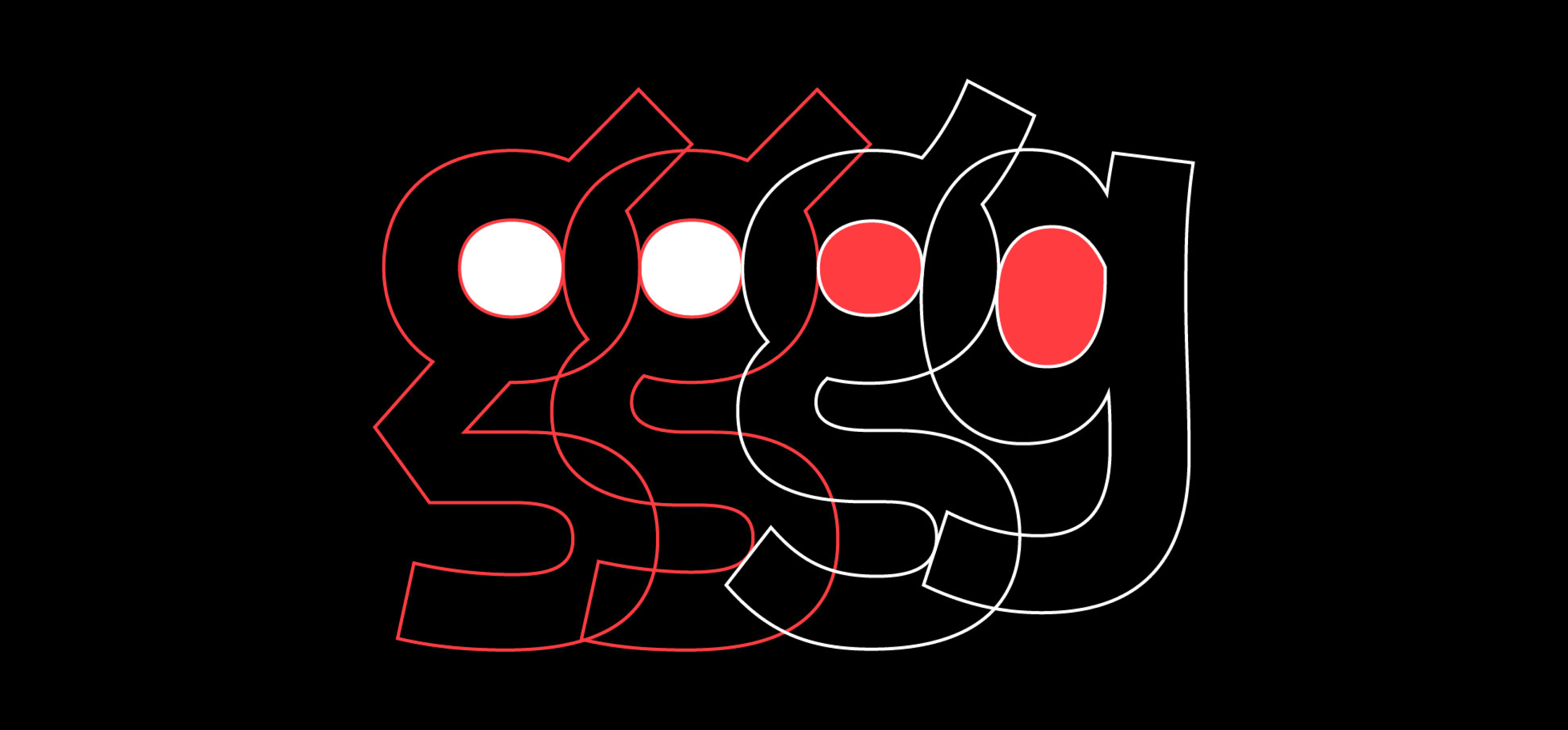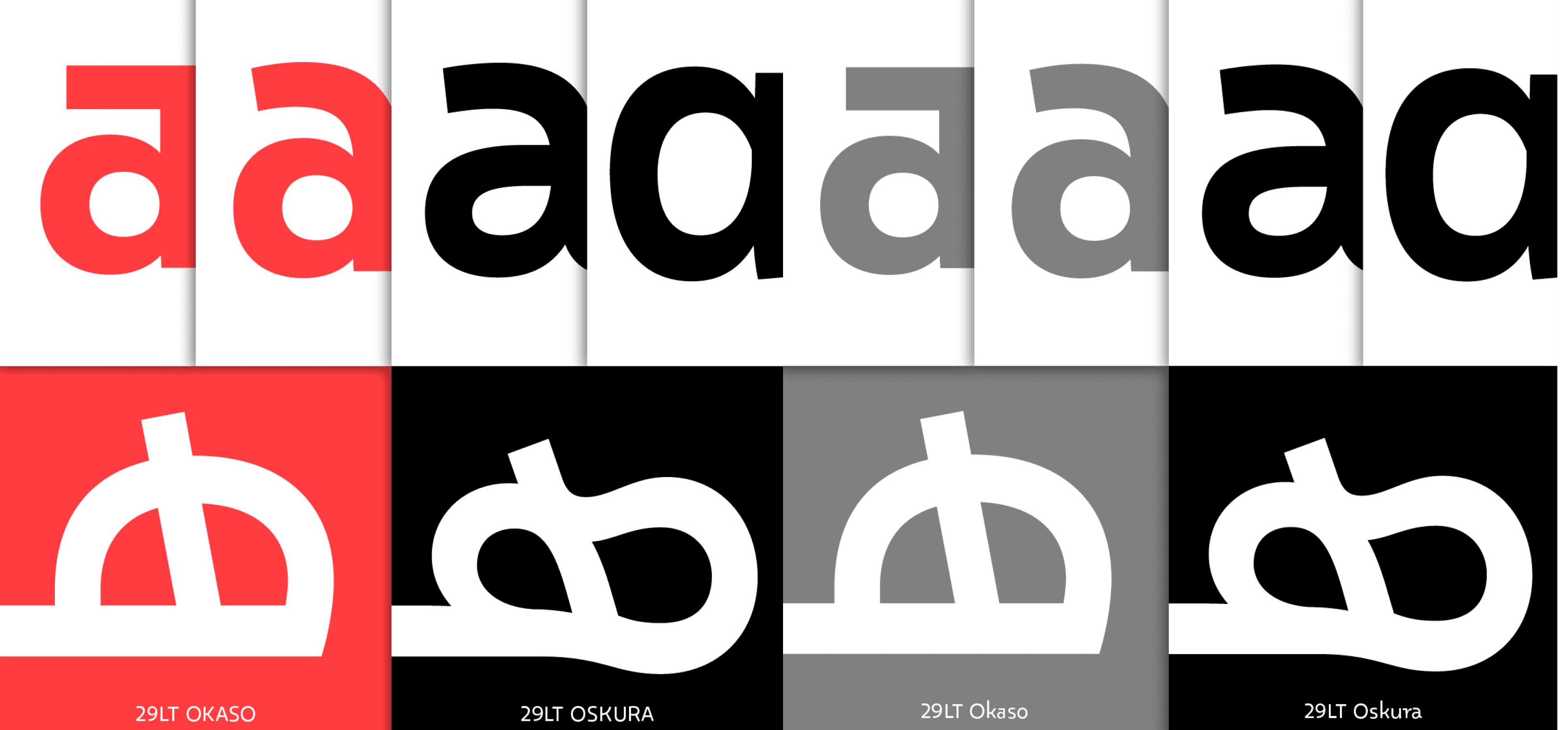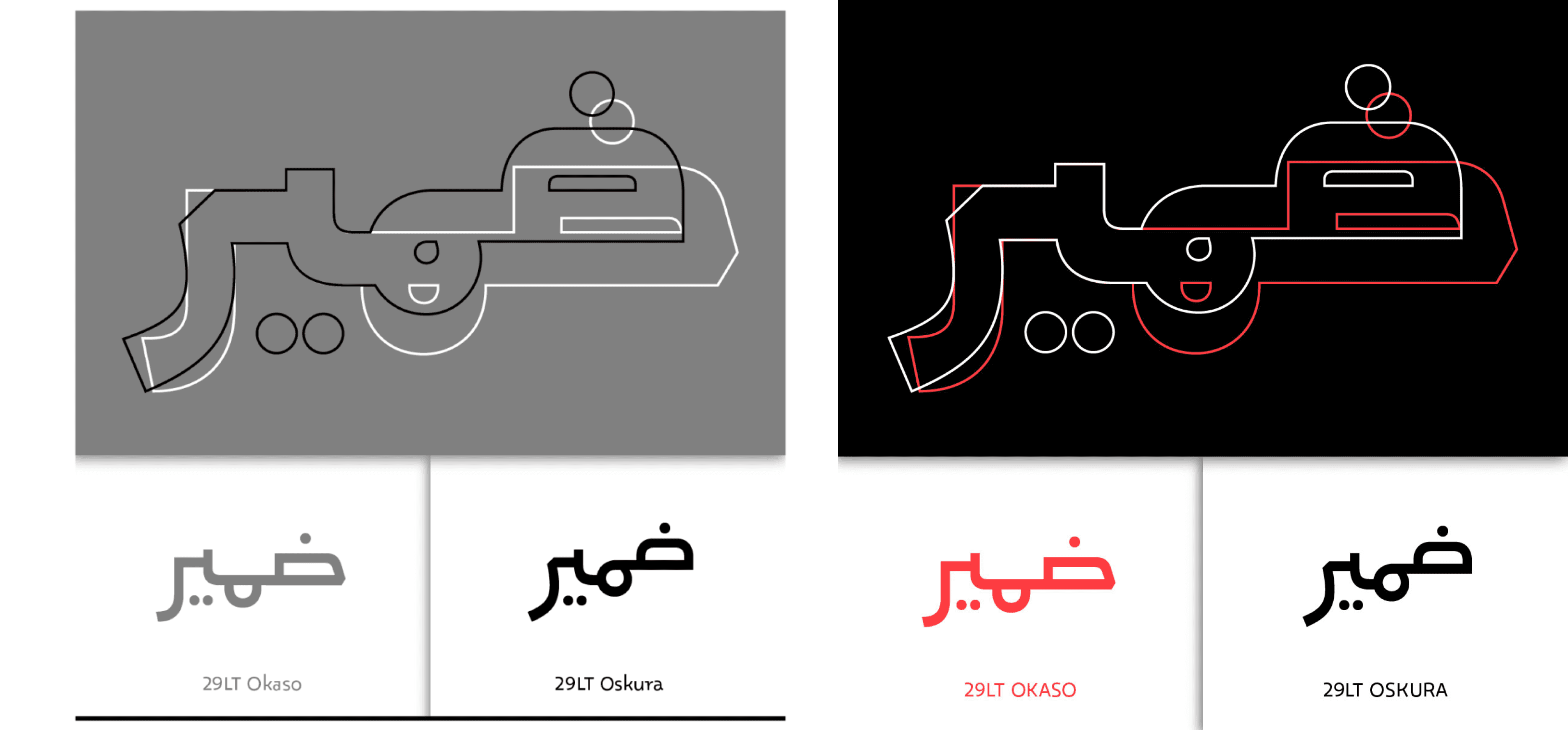
يأتي خط 29LT أَسكورا بطابع هندسي مستلهم من المخطوطات الأندلسية، حيث يمزج بين الجدية والأناقة الروحية. يتميّز بتصميم فريد يدعم وضوح النصوص الطويلة ويضفي طابعًا تعبيريًا على الكلمات، مما يجعله مثاليًا للنشر، الشعر، والمحتوى الثقافي.